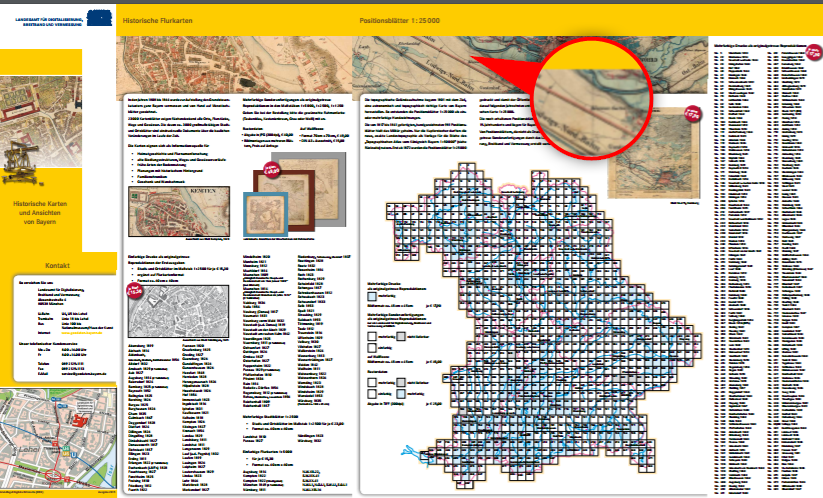
Schrift für Karten Mitte 19. Jahrhundert
Ich suche den Namen der Schriften, die im 19. Jahrhundert auf Karten verwendet wurden.
Über der Rasterkarte ist ein Ausschnitt eines Kartensegmentes die diese Schrift enthält. Da diese Firma nur historische Karten digitalisiert haben die keine Ahnung, welche Schrift das ist.
Stadtarchiv Nürnberg konnte auch keine Auskunft geben.
p.s. ich hab das auf dem PDF als Bild noch mal markiert
Die Kartenbeschriftung wurde im 19. Jhd.  von Hand ausgeführt (Kupferstich, Lithografie) und nicht in Blei gesetzt. Daher wird es nicht "die Schriften" geben, weil jede Handschrift ein wenig anders ausfiel.
Ein wenig Lesestoff dazu.
Trotzdem kram ich mal ein wenig aus älteren Strängen zum Thema zusammen, denn auch wenn das damals in mühevoller Handarbeit noch gestochen wurde, bedeutet das ja nicht, dass diese typischen Landkartenschriften nicht auch digitalisiert wurden.
Hier eine zeitgenössische Vorlage:
und hier 2 Font-Familien: